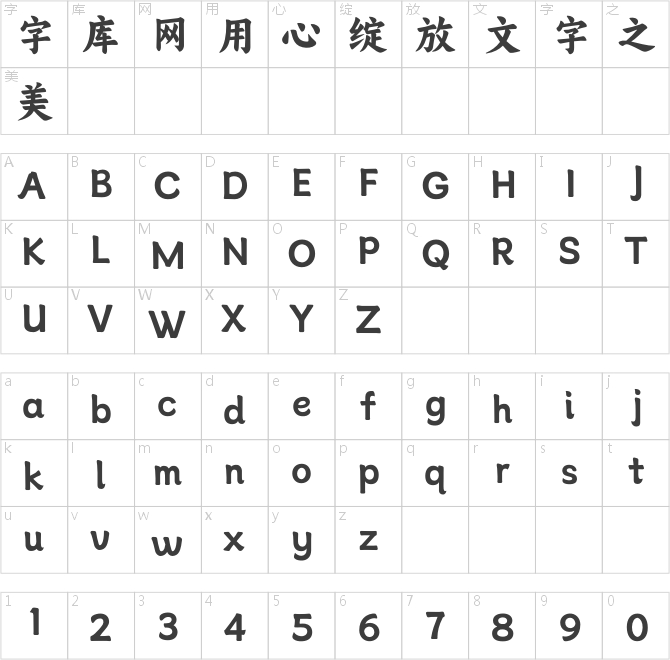
字體名稱: 阿里媽媽東方大
阿里媽媽東方大楷
阿里媽媽東方大楷介紹
阿里媽媽東方大楷是基于顏真卿的多寶塔碑算法生成并結合人力完成的一套字庫,機器學習到了顏體的豐腴厚重之感,在筆畫的描摹上做到了傳統書法的收放起伏,規范了骨架、筆畫,還原了書法中的落筆、轉筆、藏鋒、護尾等書寫韻味,使整體更飽滿、圓融、渾厚。
阿里媽媽東方大楷為中文簡體字庫,收納的中文字符包括但不限于GB2312,共計6763個漢字;英文大小寫(含全角、半角、合體字等)共105個;常用標點符號共175個,總計7043個字符。
阿里媽媽東方大楷字體字庫是一款讓人賞心悅目、百看不厭的中文字體,適合各類廣告和產品包裝設計應用,字體大小3.61MB,格式為otf字體,上傳用戶是rose,作者/版權方為阿里